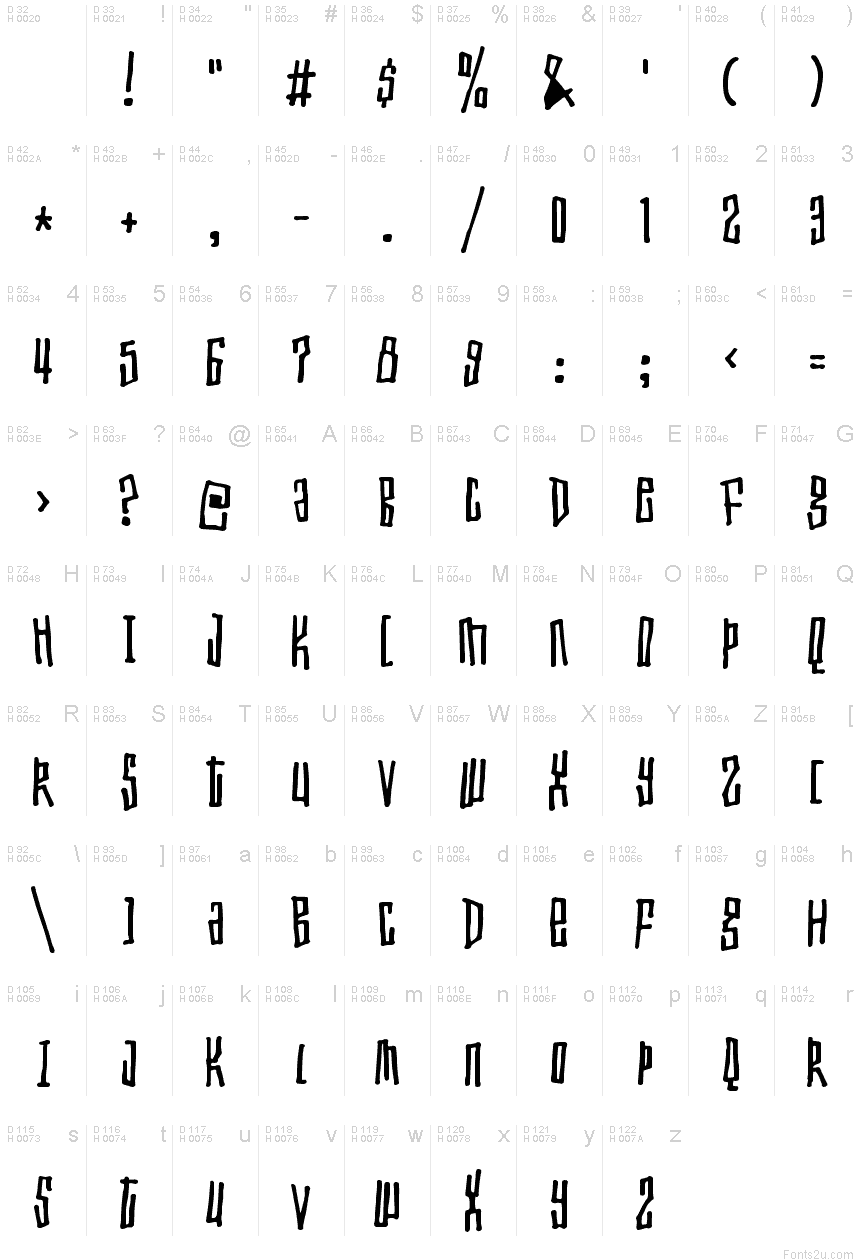
Toxic Waist od Jakuba Fischera je bezplatné, deformované písmo typu display s „ručním“ vzhledem, které působí záměrně nestabilně. Písmena sázejí na vysoké, nepravidelné tahy, měkké koncovky připomínající kapky a úzké tvary, které se chvějí přesně tak, aby celý font působil napjatě, výstředně a lehce „toxicky“.
Hodí se na plakáty, obálky zinů, undergroundové hudební letáky, titulky hororových komedií a bizarní etikety produktů, kde by čisté písmo působilo příliš upjatě. Jako bezplatný font se skvěle hodí i pro krátké nadpisy a experimenty s logy, zejména pokud chcete, aby písmena vypadala natažená, přimáčknutá a trochu „chemicky špatná“.